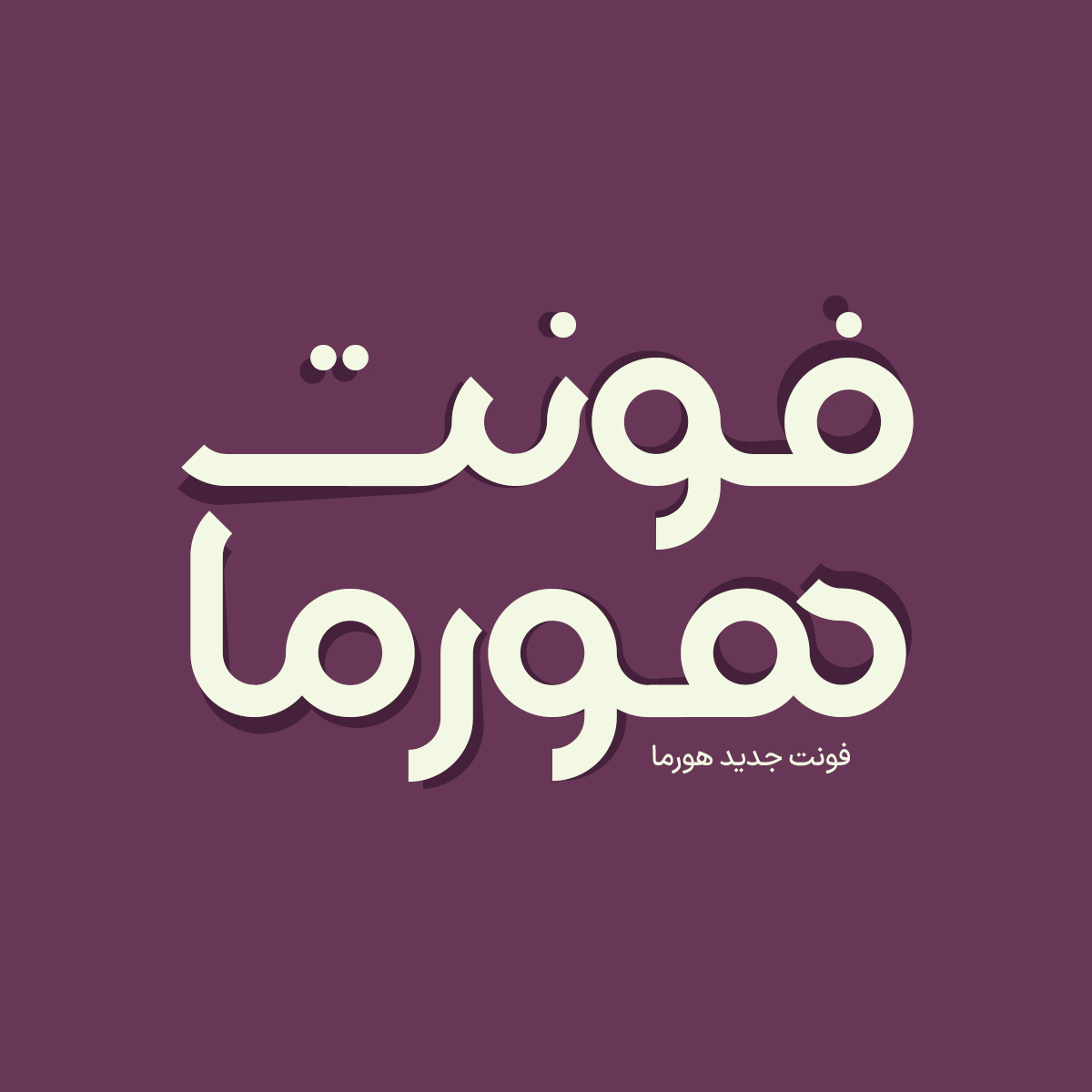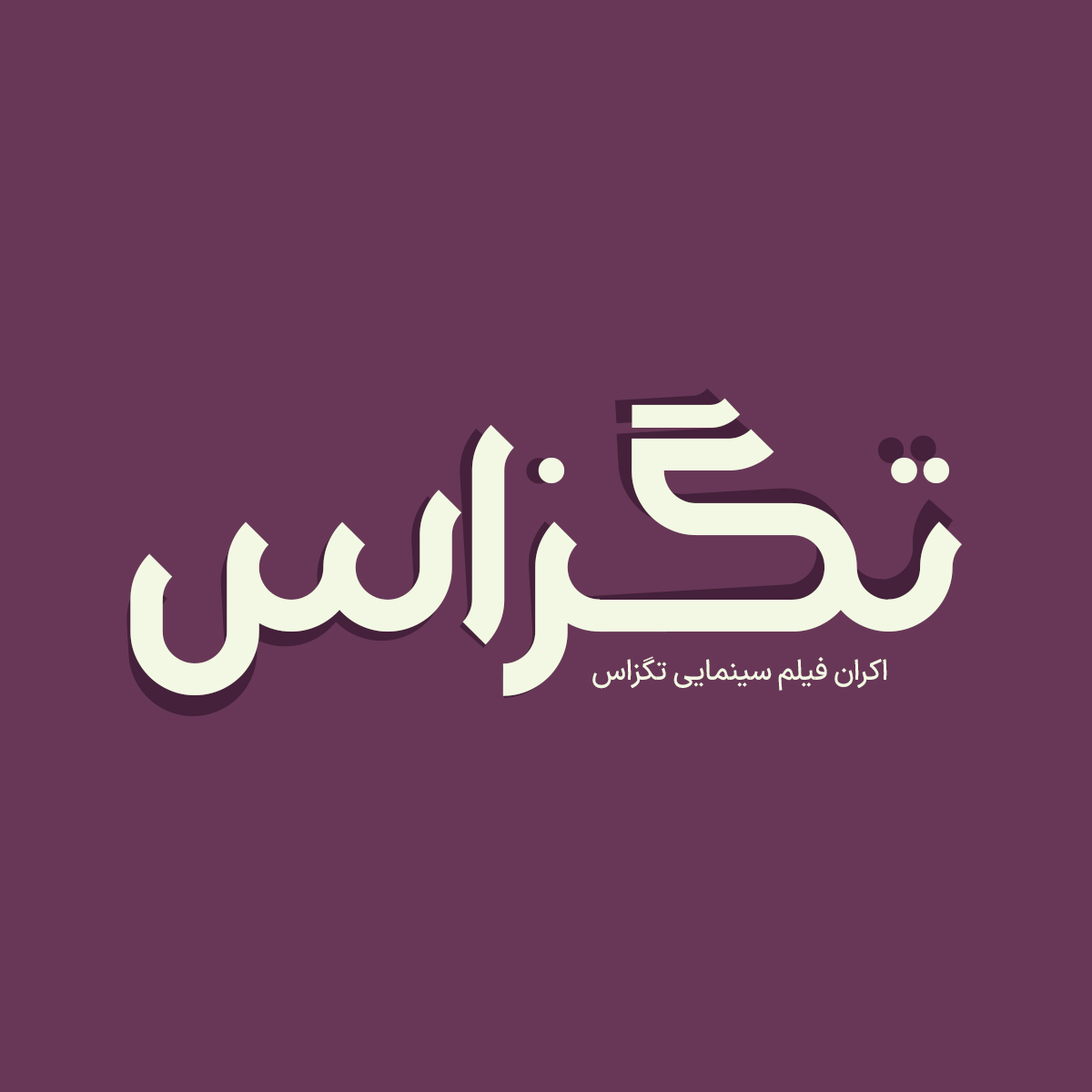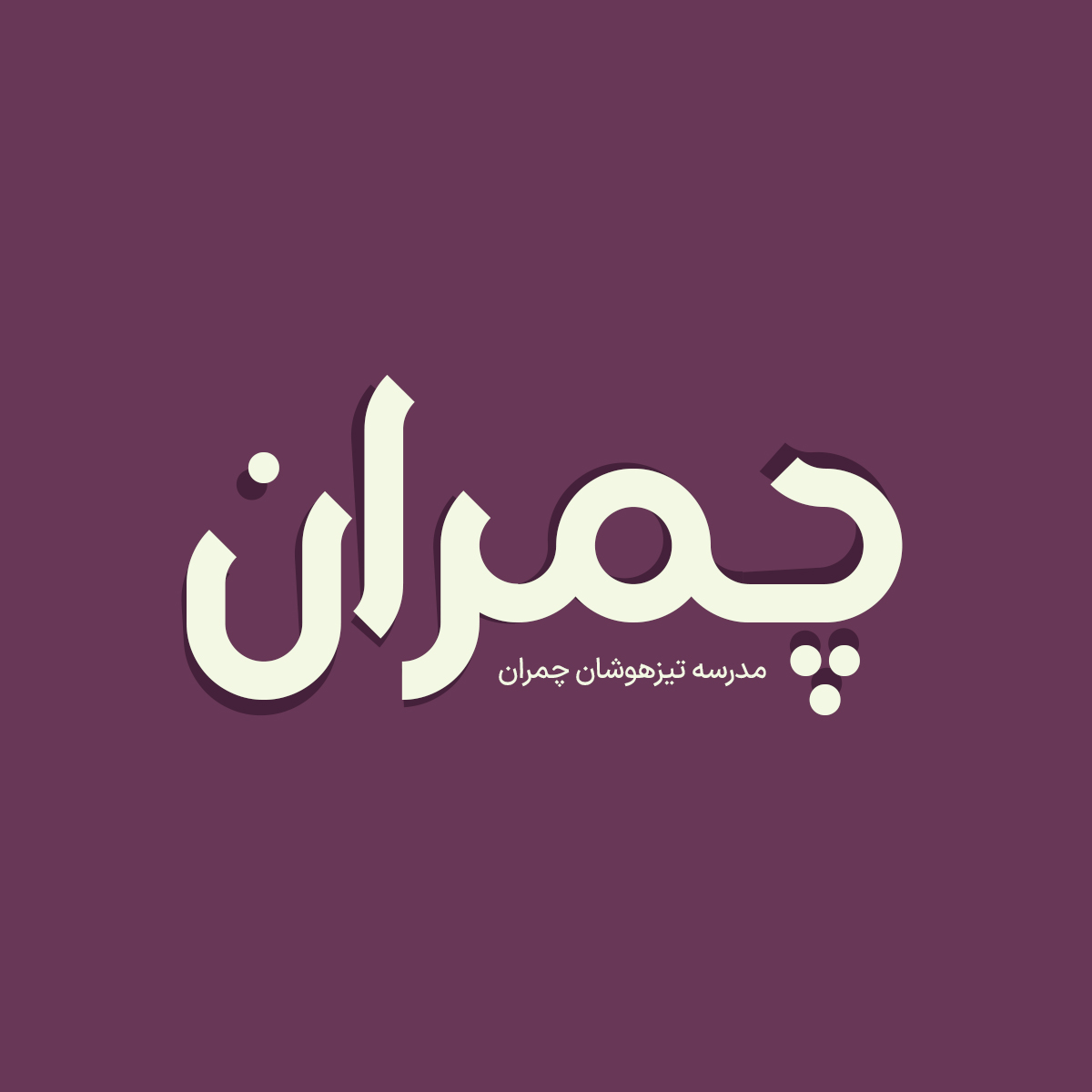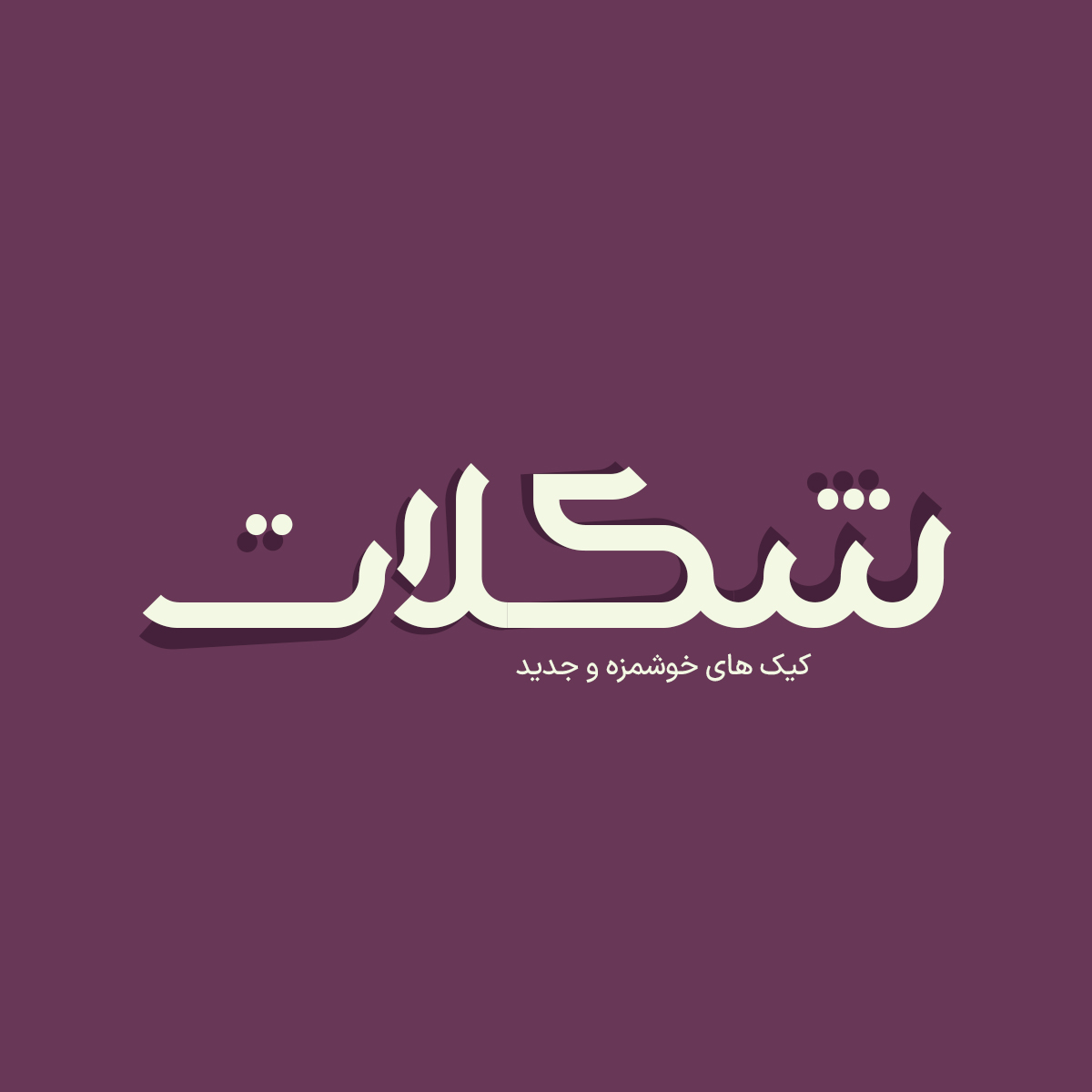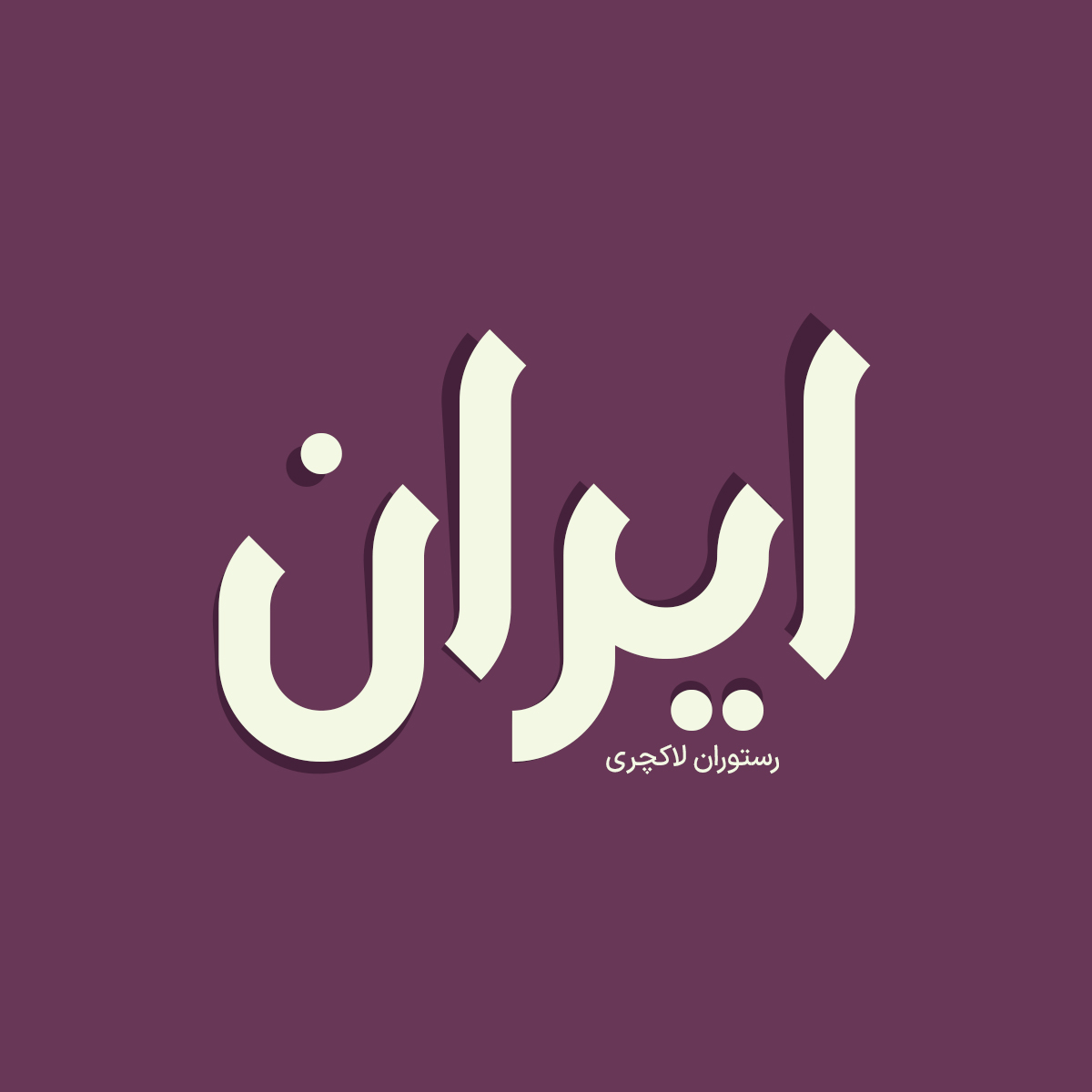
فونت فارسی هورما یک فونت فارسی بر مبنای حروف هندسی و خاص می باشد که به طراحان گرافیک امکان خلق طرح های زیبا و حرفه ای به سادگی یک تایپ میدهد.
فونت هورما دارای منحنیهای بسیار گرد با پایانه های بسیار تیز است که این فونت را زیبا، دوستانه، مدرن و خوانا میکند. فونت هورما با ارتفاع بالاتر از سایر فونتهای کلاس خود طراحی شده و برای لوگو، متنهای کوتاه و صفحه نمایش بهینه شده است. در ادامه برای شما نمونه تایپ های این محصول حرفه ای رو آماده کردیم که میتونید مشاهده کنید.
پیشنمایش و نمونه تایپ های فونت هورما